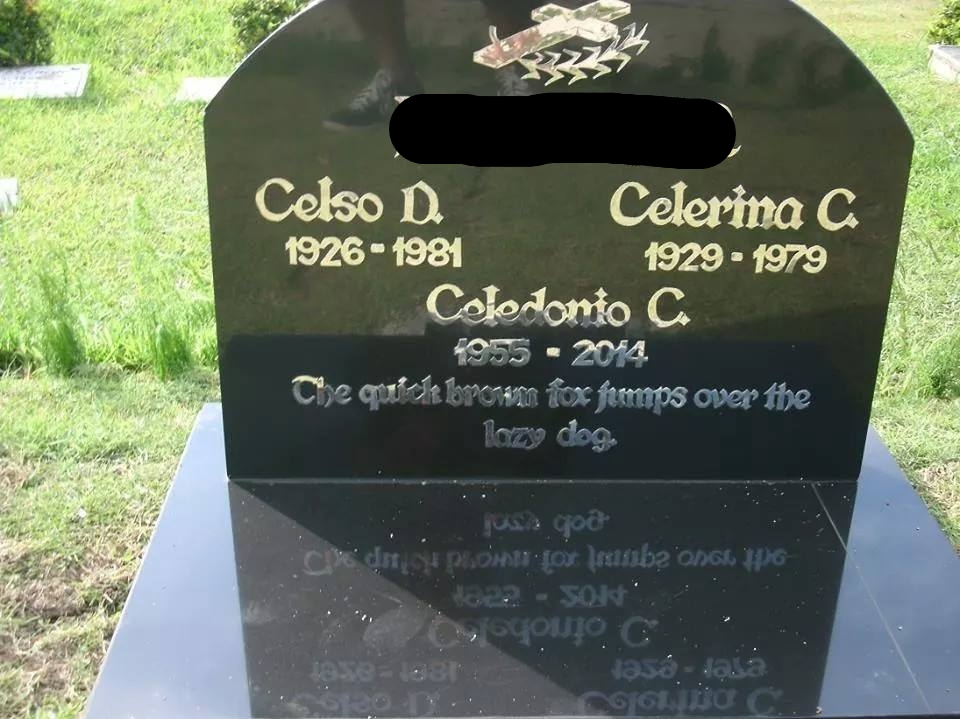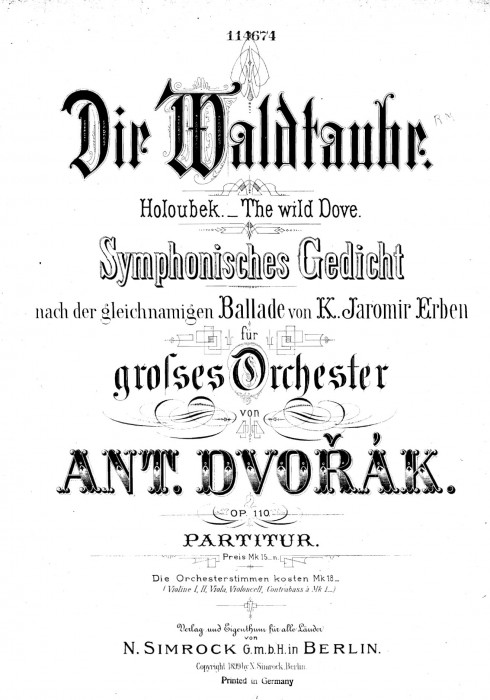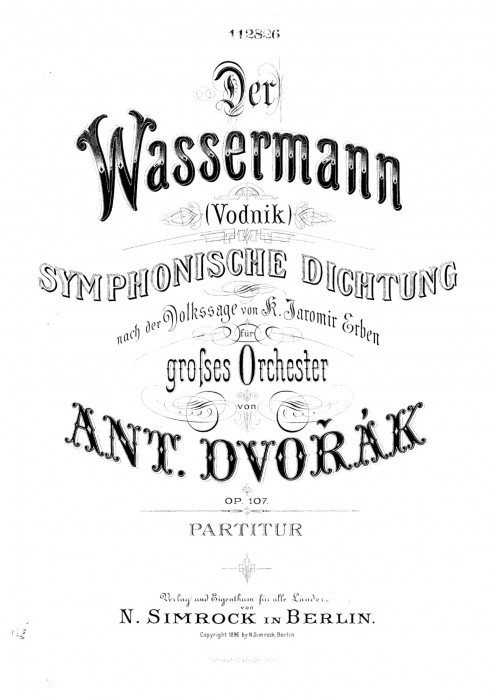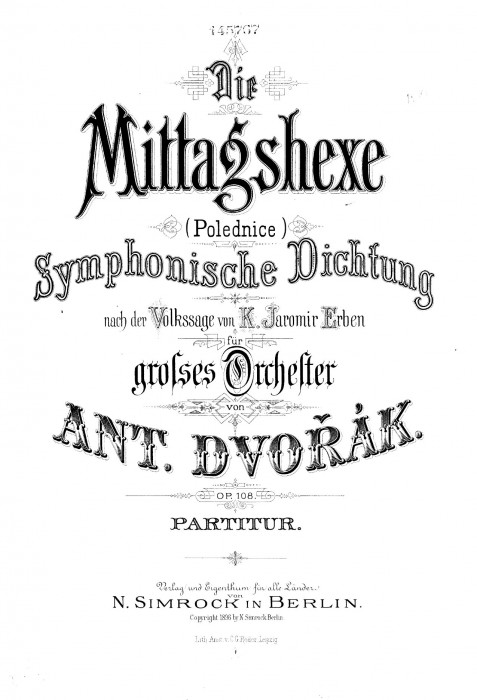
ich habe den eindruck, dass die karte, die er zeigt, auf dem sehr schlechten scan einer anderen karte basiert, auf den eine automatische texterkennung losgelassen wurde. die fehler (die tatsächlich jemandem hätten auffallen müssen) sind alles typische ocr-probleme, zum beispiel: ›belogen lassani‹ = ›belegen lassen!‹, ›Hahnclieri‹ = ›Hähnchen‹, ›Maerosirüclke‹ = ›Meeresfrüchte‹ oder ›richIg und rechizellig‹ = ›richtig und rechtzeitig‹. vermutlich war das original auch schon nicht komplett fehlerfrei, aber zumindest besser lesbar als das gezeigte exemplar. die pizzeria gibt es übrigens nicht mehr. da ist jetzt eine andere.
Hmm? Pizzeria Americana in fetter Fraktur empfinde ich dann aber auch als "überaus passend" :hammer:  Wo diese Schrift doch so überaus italienisch und amerikanisch zugleich ist.
Und noch ein Blindtext-Unfall …
Das ist ja auch vom Blindtext abgesehen mehr oder weniger ein Typographie-Unfall.
Ich kann’s kaum glauben, dass das ein echter Grabstein ist.  :shock:
Vielleicht war einer der Verblichenen der Erfinder dieses Blindtextes?
prokrastinationsfeierabend: celedonio könnte ein philippinischer nachname sein. «the quick brown fox» (jumps over the lazy pig) war – laut dieser website – eine 1980 ebenda veröffentlichte filmkomödie … celedonio c. könnte also ein halt doch nicht ganz unsterblicher filmfan gewesen sein. oder so.
Vielleicht war einer der Verblichenen der Erfinder dieses Blindtextes?
prokrastinationsfeierabend: celedonio könnte ein philippinischer nachname sein. «the quick brown fox» (jumps over the lazy pig) war – laut dieser website – eine 1980 ebenda veröffentlichte filmkomödie … celedonio c. könnte also ein halt doch nicht ganz unsterblicher filmfan gewesen sein. oder so.
Zumindest der Text zur Quelle steht diesen Vermutungen entgegen.
Ob typografisch ein Verbrechen oder nicht: ich persönlich kann mich an diesen Titelseiten einfach nicht satt sehen!
Das mußte einfach mal raus! :party::ilovetype::bandit:
Sind übrigens alle vier (1, 2, 3, 4) mit extrem düsteren Inhalten. Da soll noch mal einer sagen heute handele alles nur von Mord und Totschlag!
Nun, die Sache mit der typografischen Straftat bmuss man einfach aus der Zeit heraus betrachten, und da war es einfach blich so, egal ob euine Anzeige, oder gar das Titelblatt eines wisseenschaftlichen Buchs, man hat da einfach total unbefangen mit den Schriftarten gesipelt, und dann alles Verschnörkelt, bis der Stichel glühte.
Das sah in Architektur, oder selbst im Maschinenbau ja nicht anders aus. Selbst Fabrikhallen hatten verschörkelte Zierelemente.
Rein vom Handwerklichen ziehe ich meinen Hut, egal ob da jetzt die Druckplatte derart in Kupfer oder bei großauflagen in Stahl gestochen wurde, oder ob solches als Monogramm auf 96 Besteckteilen prangte, schließlich ist das alles in größter Präzision, die am PC nachzubauen schon immens Arbeit ist ja alles von Hand grestochen worden, wqöhrend man sich heute bei 5 ziemlich schlichten Buchstaben eines Firmenlogos auf die Suche nach einem Font macht, anstatt die schnell zu zeichnen.
Ich glaube, so manch einer der damaligen Kupferstecher würde heute ungläubug den Kopf schtteln, über das, was wir heute so veranstalten, und darin oft ein größeres typo-Verbrechen sehen, wie heute oft mit Schriften umgegangen wird.
Heutzutage würde man solche Schmankerl wohl nicht mehr als Deckblätter für Noten fertigen – sondern als Schriftmusterbögen.  ;-)
Gefällt mir :-) Erinnert mich an die knackigen Salate, bei denen ich das erste n vergessen hatte. Aber der gesamte Text auf dem Etikett ist meiner unbedeutenden Meinung nach für den Arsch, da passt’s wieder. "Kokette Würze" … "glockenklar in der Struktur" … wusste nicht, dass man Wein auch rauchen kann.
Im allgemeinen kann man aber ohnehin davon ausgehen: Je mehr schmalziges Bla Bla  auf dem Etikett, um so eher ist der Inhalt der Buddel billige Plörre. Also hätte icvh den Fehler kaum mitbekommen, da schon bei den esten Worten die Flasche wieder im Regal stehen würde.
Wer einen Merlot erklärt bekommen muss, ist zurecht orientierungslos.
Supi! Dann kann ich beim nächsten Weinkauf ja beruhigt zum billigsten Merlot greifen – wenn die alle gleich schmecken. :baeh:
SCNR   :aschehaupt:  Ich weiß natürlich, was du eigentlich meinst.
Das muss nicht immer falsch sein. Es liegt zwar schon einige Zeit zurüch, als im TV verschiedene Weine verdeckt vekostet wurden (von zufälligen Passanten wie von Profi Sommeliers, und da schnuitt dann überraschenmderweise  ein preiswerter Discounter-Wein besser ab, als eine 30€ Sorte vom speziellen Weinhandel.